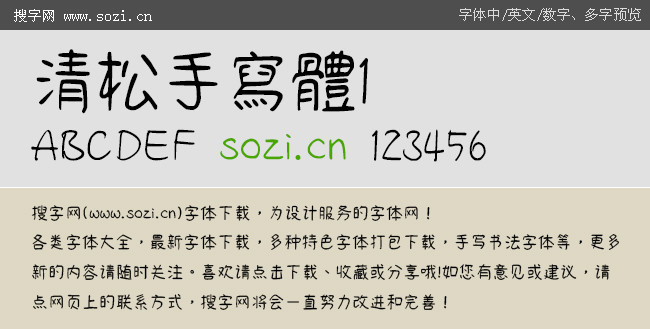
清松手寫體1
搜字網(wǎng)給大家提供一款清松手寫體1中文藝術(shù)字體下載,清松手寫體1字體是一款支持簡體輸入法也支持繁體輸入法使用的藝術(shù)字體,字體字形規(guī)矩大方、字體粗細均勻、字形圓潤、形象漂亮。適用于包裝設(shè)計、海報設(shè)計等廣告設(shè)計應(yīng)用。